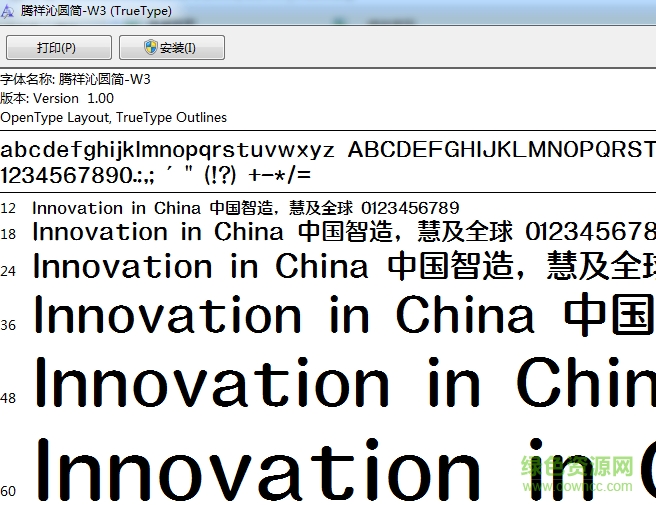
騰祥沁圓簡 w3
騰祥沁圓簡w3字體騰祥字體庫中的一款簡體字體,字體具有非常鮮明的個性,從許多小的細節(jié)之處便可看出,超炫的設(shè)計,讓廣大朋友們能夠享受自字體的魅力。有需要的朋友就來綠色資源網(wǎng)下載吧!
騰祥沁圓簡w3字體
騰祥沁圓簡w3字體是一款簡體中文字體,該字體線條較之前兩款字體稍微要粗一點,卻更有韻味,有需要的朋友就趕快來綠色資源網(wǎng)下載吧!